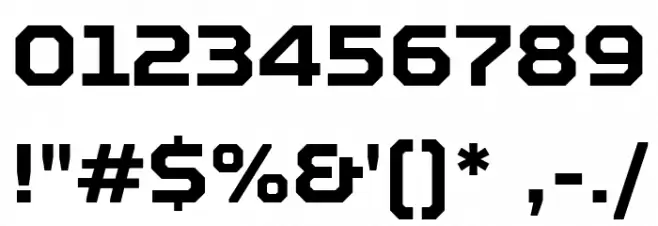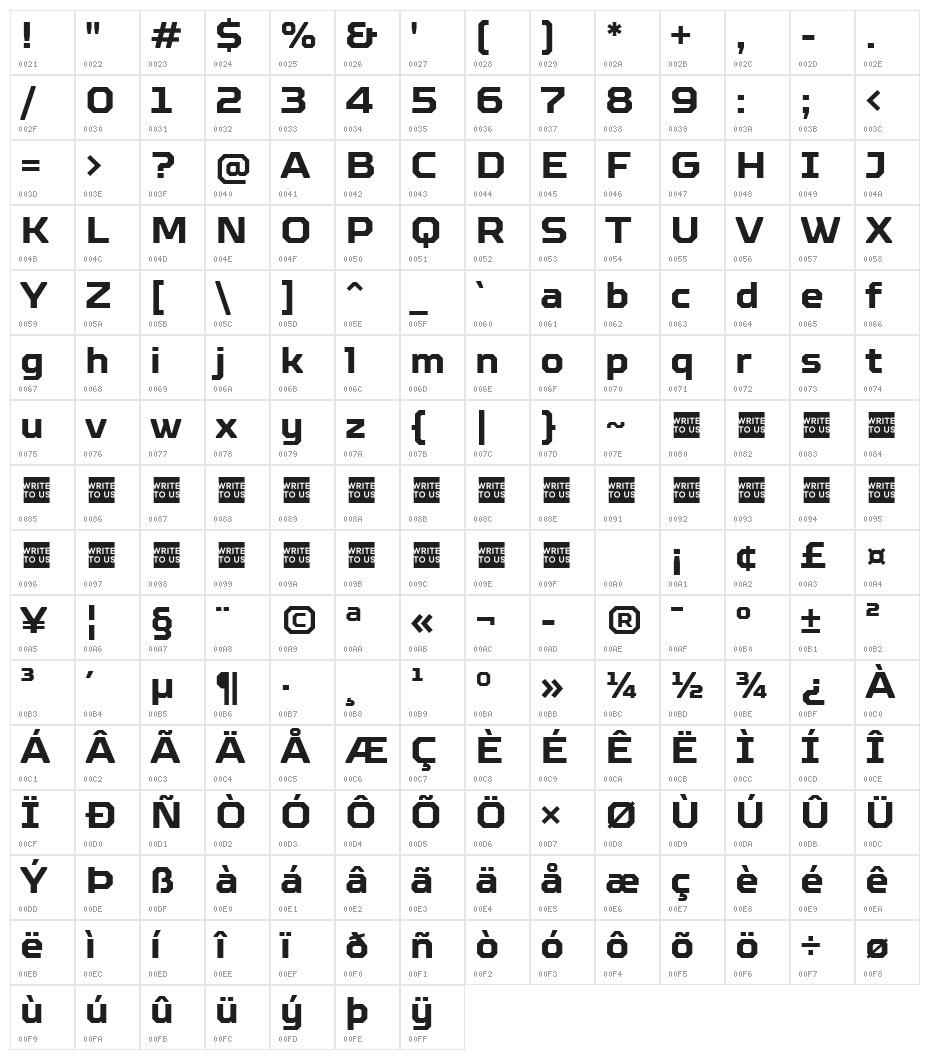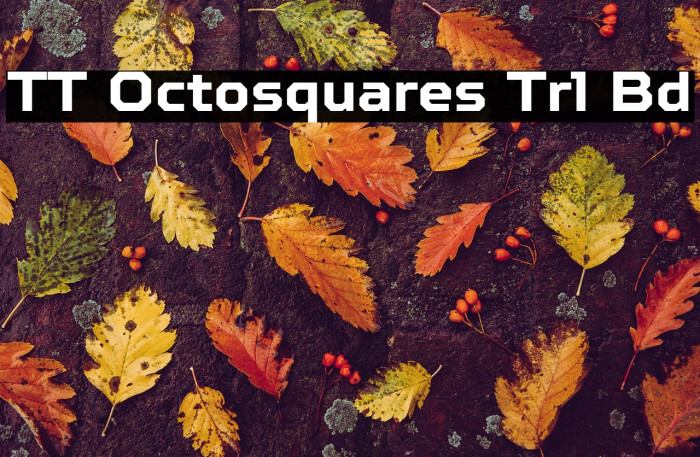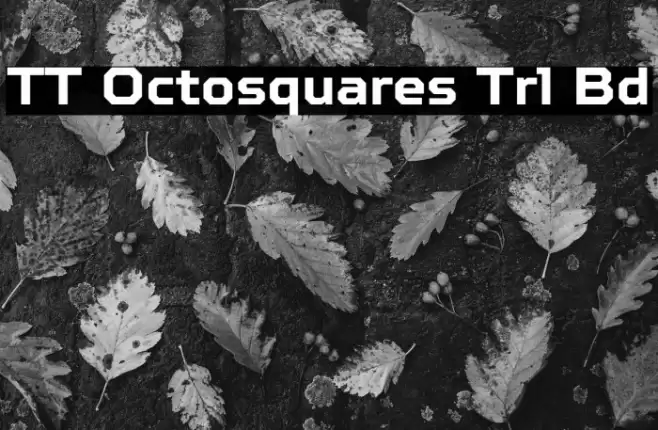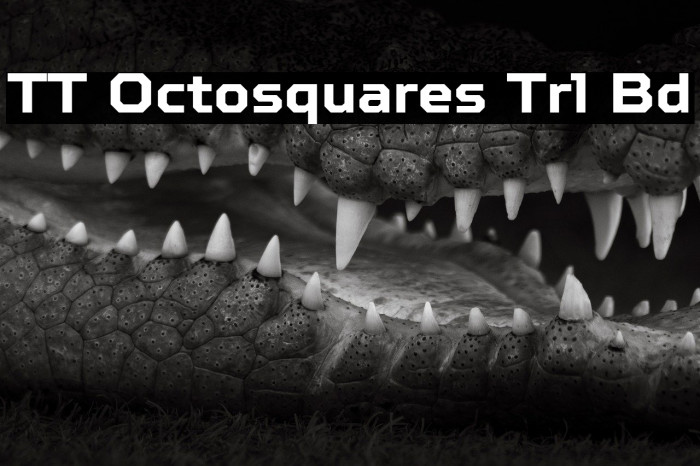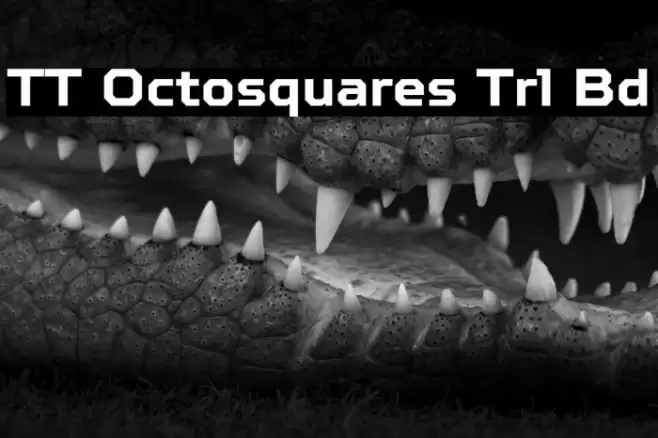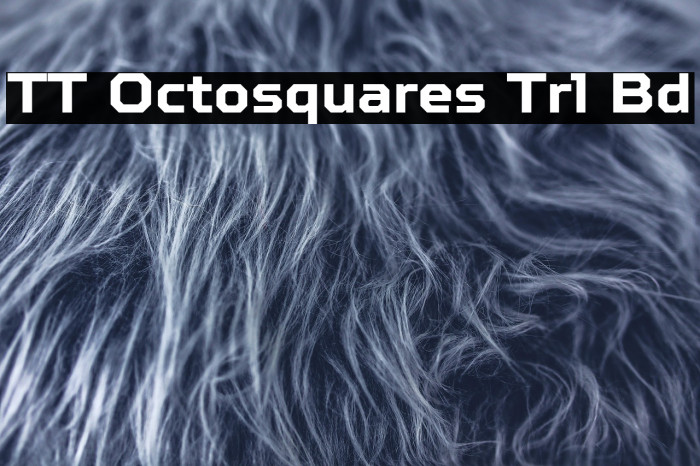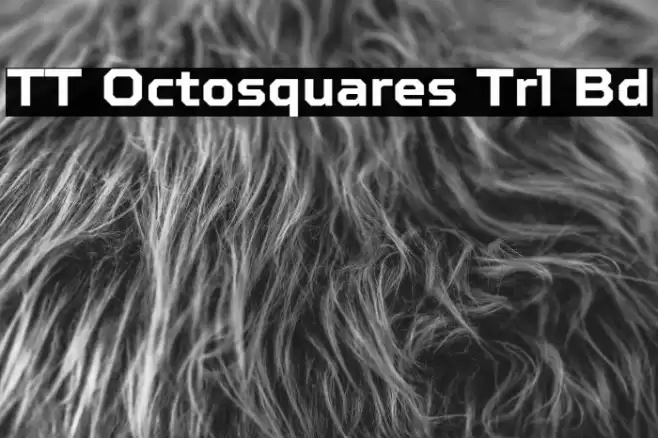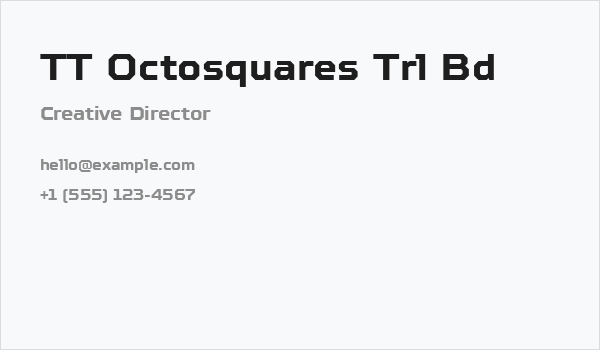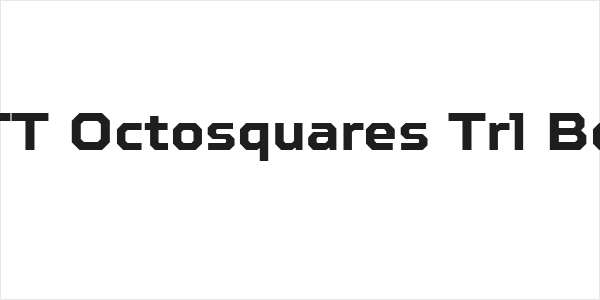
TT Octosquares Trl Bd Font
Fonts by TypeType Foundry
| Nome | TT Octosquares Trl Bd |
| Família da fonte | TT Octosquares Trl |
| Projetos propostos | Ideal for branding, headlines, posters, and digital interfaces where a modern and bold statement is desired. |